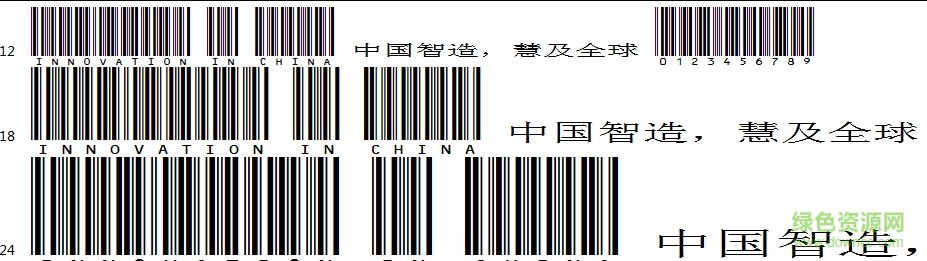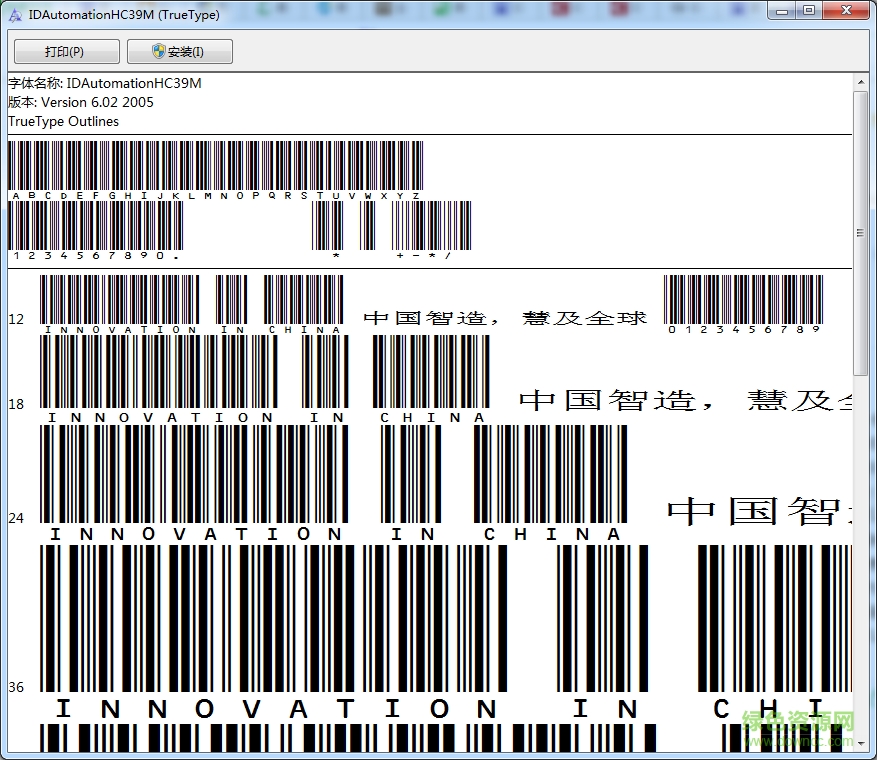
IDAutomationHC39M是一款非常好用的條形碼字體,字體簡(jiǎn)單應(yīng)用領(lǐng)域廣泛,能有效掃描識(shí)別多種條碼信息??靵砭G色資源網(wǎng)下載體驗(yàn)吧!
IDAutomationHC39M是一款條形碼字體軟件,在條形碼字體印刷設(shè)計(jì)方面有著不錯(cuò)的應(yīng)用